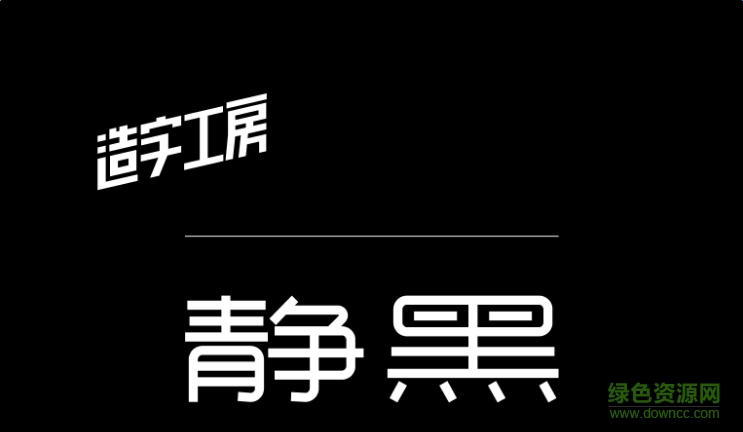
造字工房静黑体是一款造字工房类清新简洁风格字体软件,静黑字体一笔一划直爽有力,整体效果显得扁平有创意,深受广大书法家喜爱,还有更多好看字体欢迎来绿色资源网下载体验!
造字工房静黑体,其字形扁平,此款字体在黑体字形基础之上巧妙创新,笔画纤细、简洁有力、字形简约、风格明显且易于阅读。结构清晰紧密而内敛,给人清新脱俗之感。